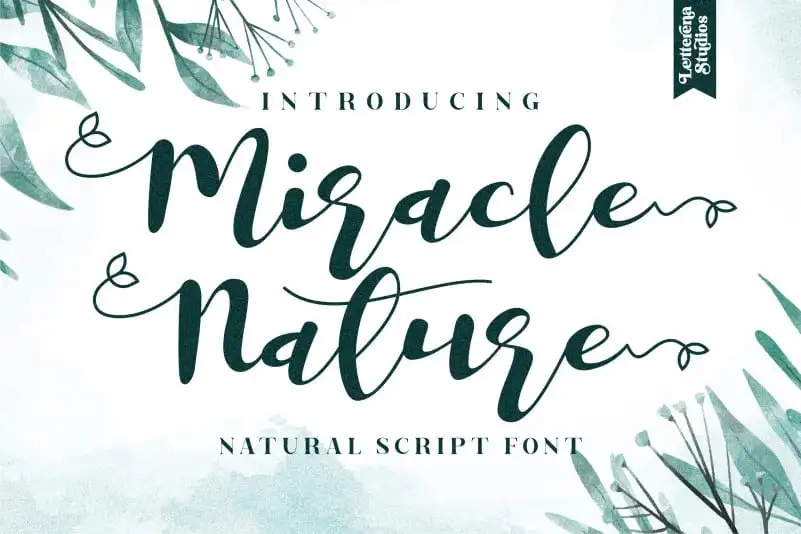
Miracle Nature Calligraphy Font – Download Grátis
A fonte ‘Miracle Nature Calligraphy Font’ é uma escolha perfeita para quem busca tanto charme quanto elegância em suas criações digitais. A sua natureza inspiradora não apenas reforça a beleza intrínseca dos design gráficos, mas também transmite um toque delicado e autêntico. Este script de qualidade é especialmente adequado para aplicar em eventos festivos como casamentos, agradecimentos, cartas de citação, cartões de boas-vindas, logotipos e cartões de negócios. Além disso, ela é perfeita para qualquer tipo de design que busque incorporar um toque autêntico e humano, como por exemplo, em criações publicitárias ou design editorial. Com ‘Miracle Nature Calligraphy Font’, você consegue trazer uma dose única de personalização aos seus trabalhos digitais.